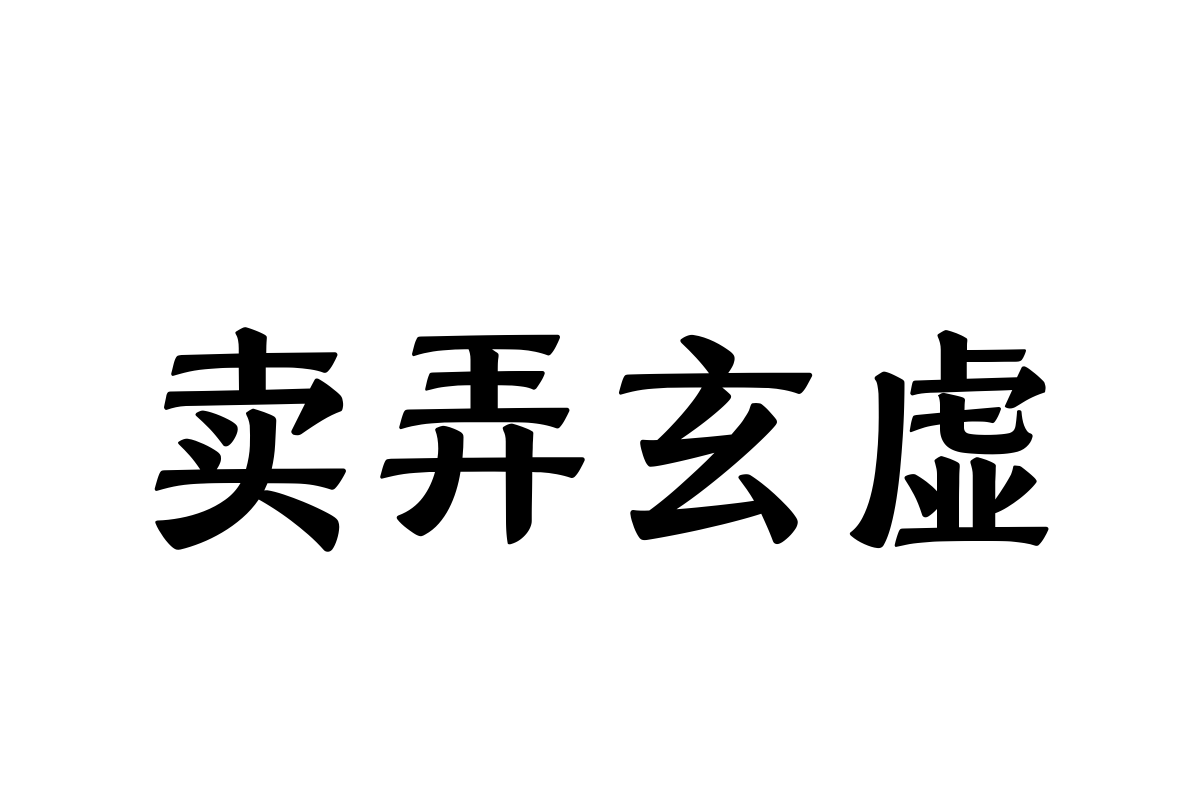
永字夏蝉75j是一款由汉仪公司设计的字体,具有独特的风格和特点。这款字体的特点是线条流畅,笔画粗细均匀,结构简洁明了,给人一种清新自然的感觉。同时,它的字形规整,易于阅读和识别,适用于各种印刷品和设计作品。
永字夏蝉75j的字体大小为75号,适合用于标题、副标题等需要强调的场合。此外,这款字体还具有很好的适应性,可以应用于各种类型的文本,如新闻、广告、书籍、杂志等。
总之,永字夏蝉75j是一款实用性强、美观大方的字体,适合用于各种需要强调的文字设计。